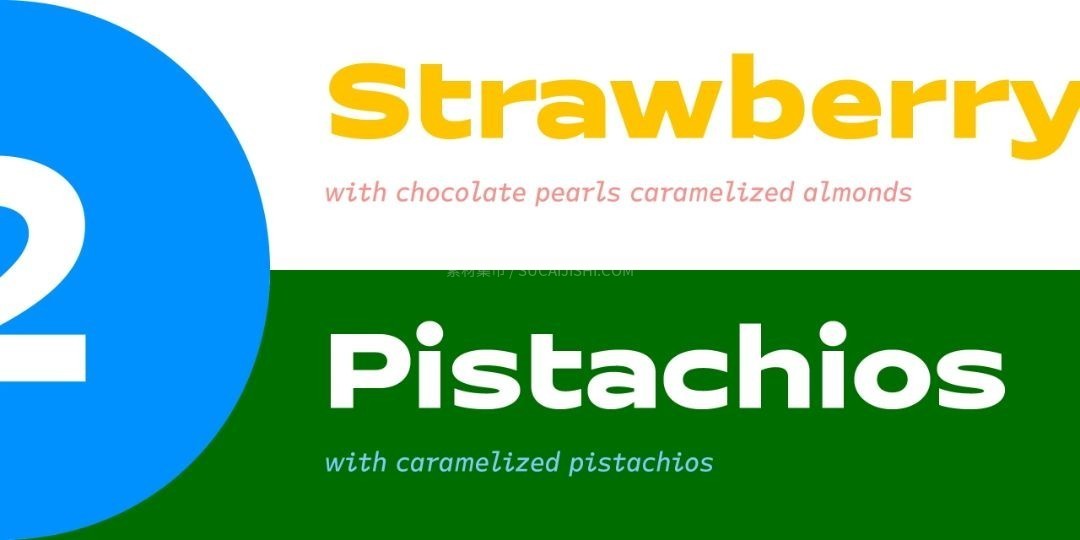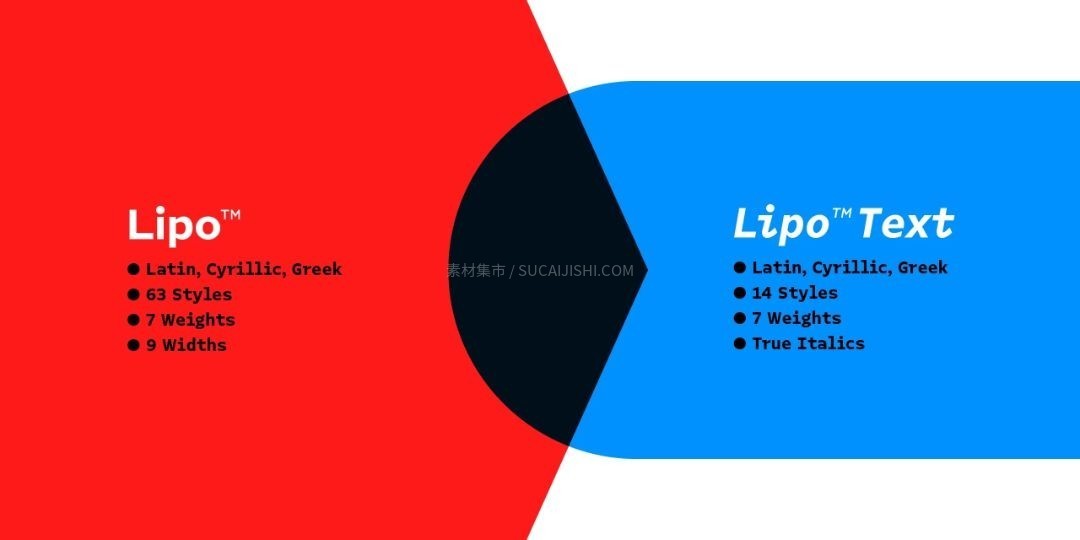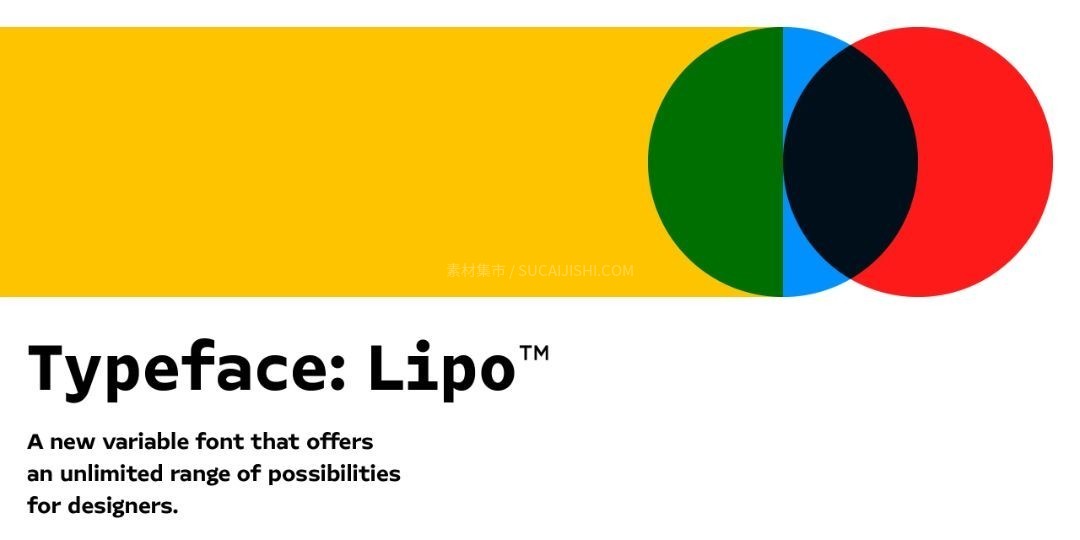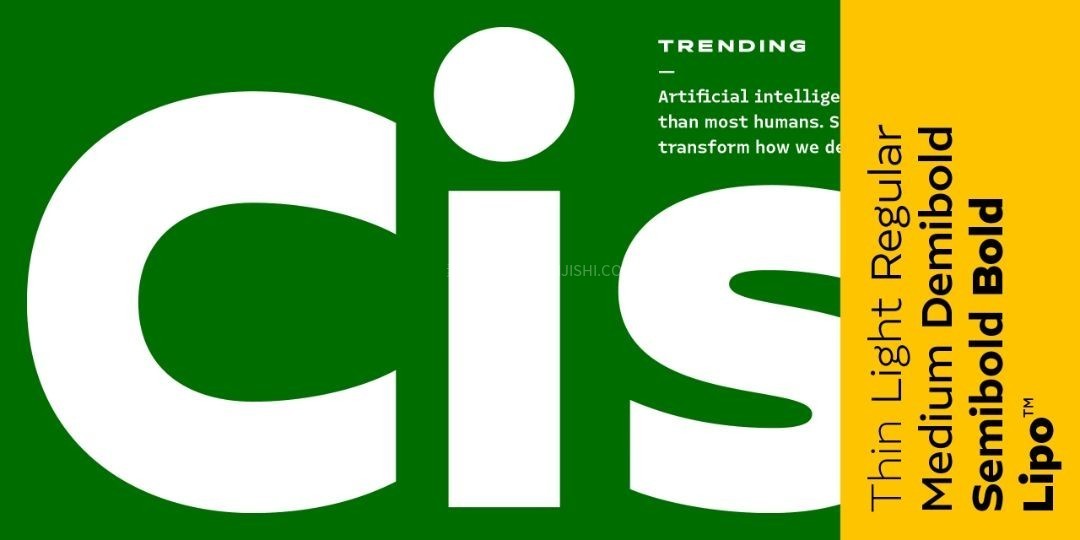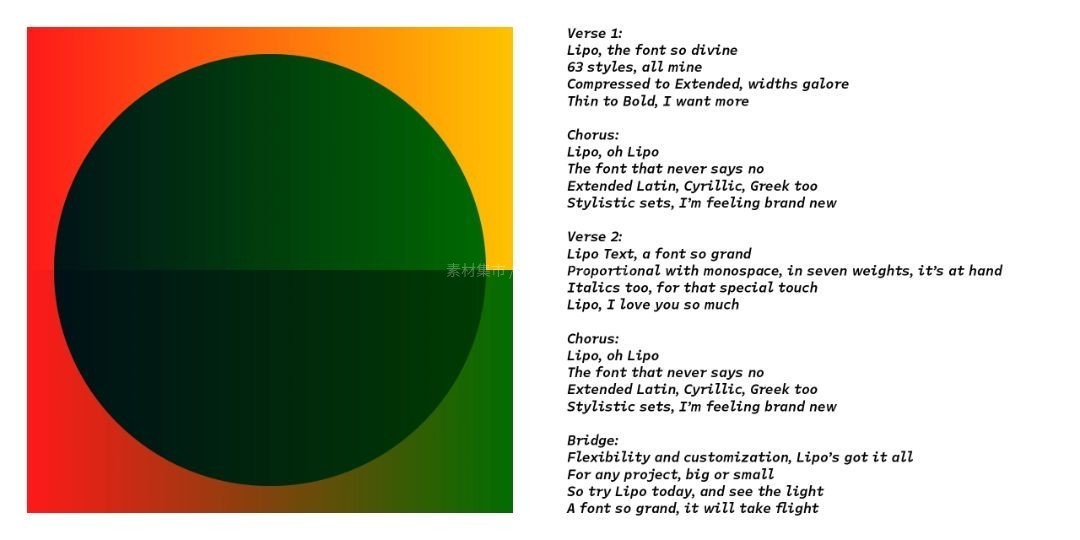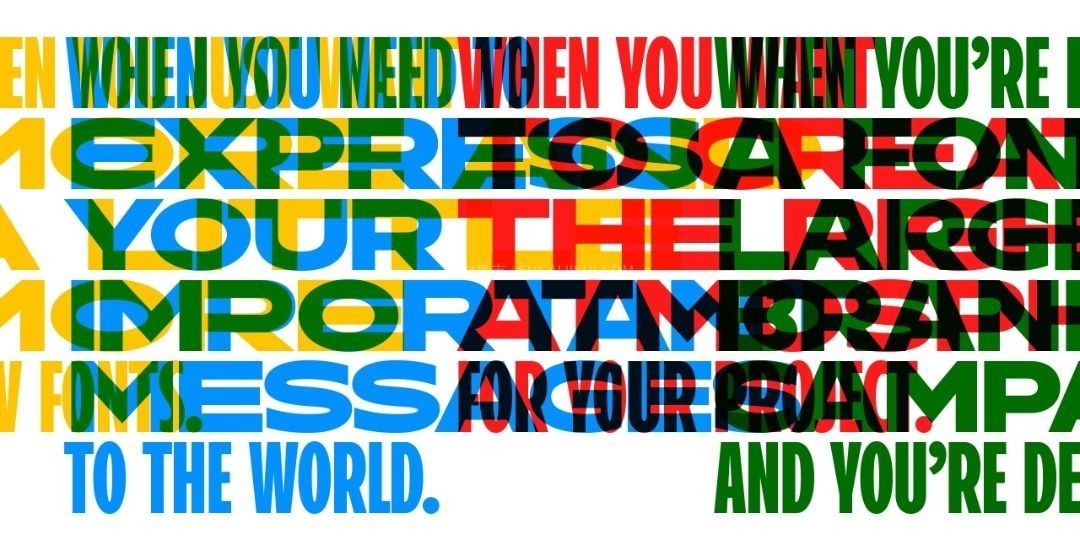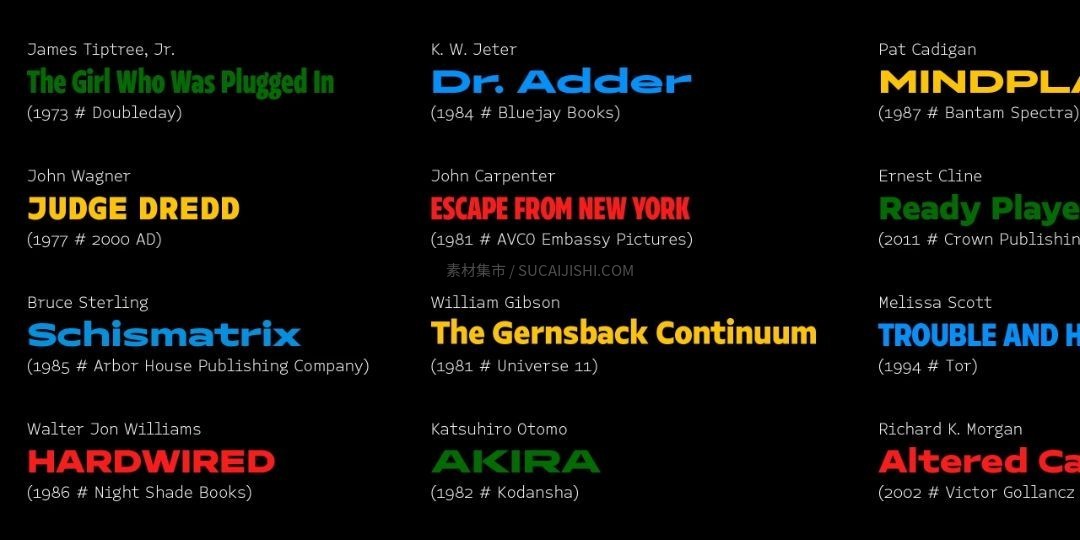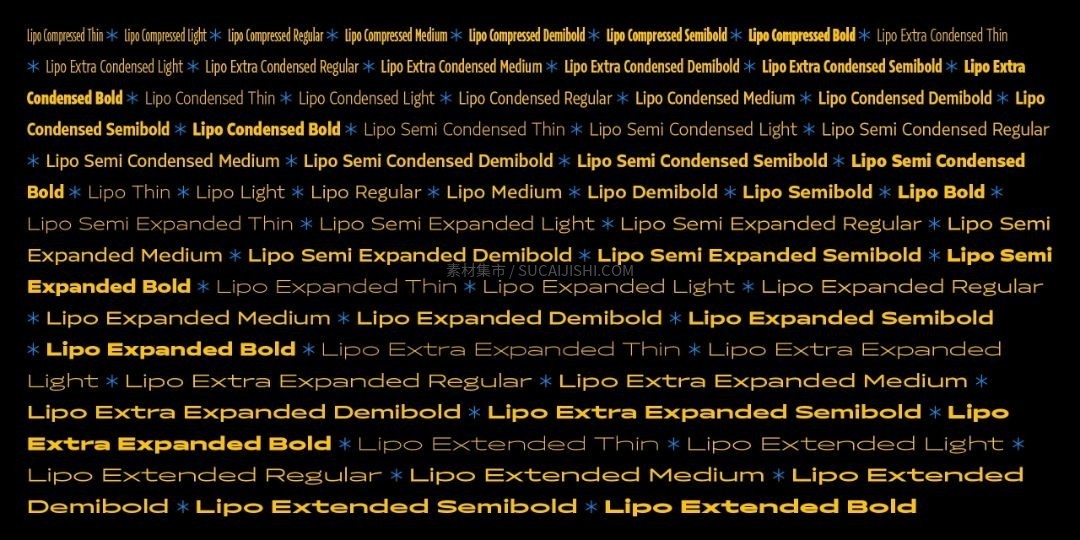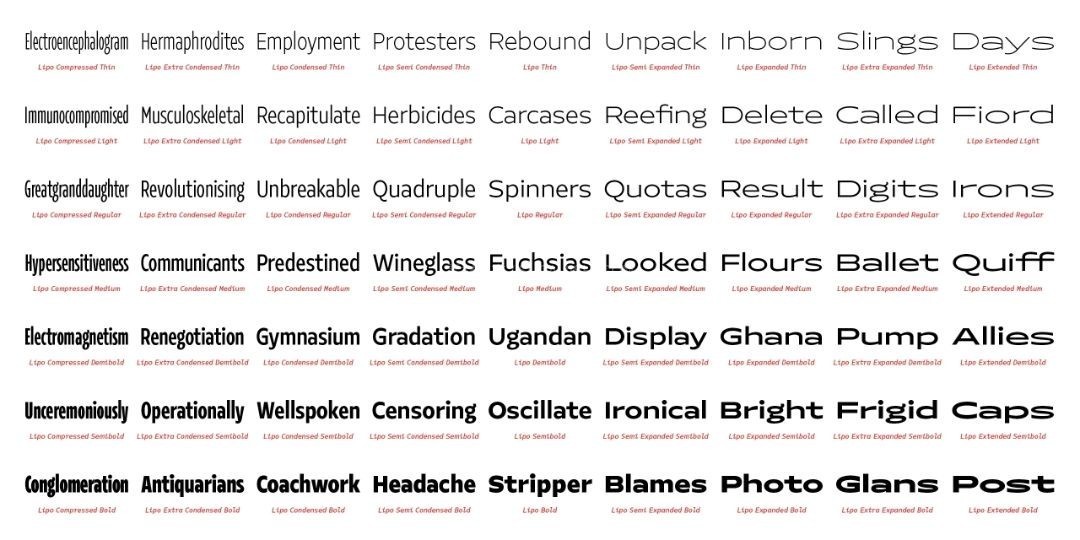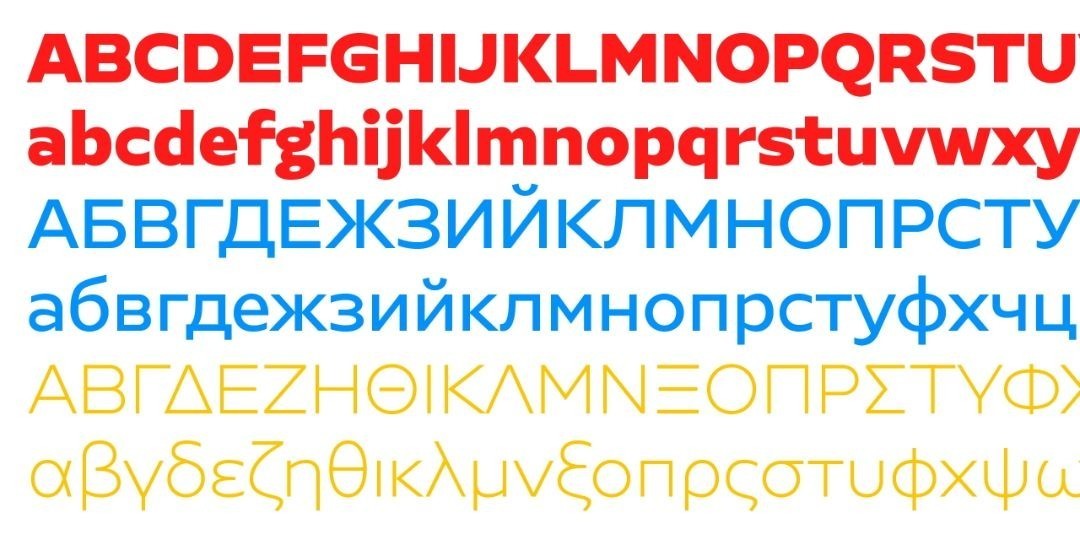
Lipo现代无衬线西文字体家族
Lipo 是一款专为极致设计灵活性而打造的高可变性西文字体系统,包含 63 种字形样式与 14 种文本样式,提供 OTF、TTF 及 Web 网页字体格式。其设计横跨 9 种字宽(从极窄压缩到超宽扩展)与 7 种字重级别,并支持扩展拉丁文、西里尔文及希腊字母等丰富字符集,配合强大的 OpenType 替代字符与样式集功能,能完美胜任跨语言国际传播与多样化的现代排版需求。